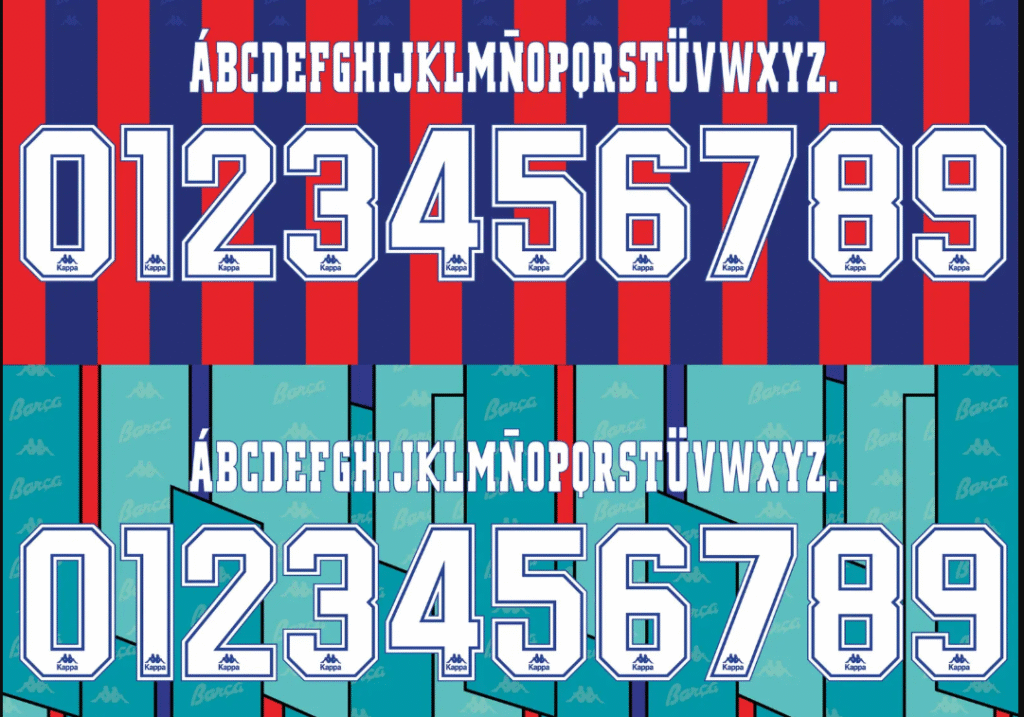
Fonte FC Barcelona 1995-1997 (Kappa) – A Era Ronaldo Fenômeno | Download TTF
Se existe uma época dourada que desperta a nostalgia de qualquer torcedor Blaugrana, é o meio da década de 90. Sob o comando da fornecedora Kappa, o F.C. Barcelona desfilou nos gramados europeus com uniformes que se tornaram verdadeiros ícones da cultura do futebol.
Neste post, trazemos para você a tipografia lendária utilizada entre as temporadas de 1995 e 1997. Esta é a fonte que estampou as costas de lendas como Pep Guardiola, Luís Figo, Stoichkov e, claro, a temporada avassaladora de Ronaldo Fenômeno (1996/97). É o arquivo essencial para quem deseja recriar com perfeição a magia do Camp Nou daquele período.
Estilo Visual: A Estética Clássica da Kappa
A tipografia do Barcelona dessa era reflete a identidade visual marcante da Kappa nos anos 90. Trata-se de uma fonte robusta, com serifas grossas e uma estrutura geométrica sólida (“block font”).
Visualmente, ela transmite força e tradição. Nos uniformes titulares (listras verticais Azul-Grená), os números eram geralmente aplicados em branco, muitas vezes com um sombreamento ou contorno preto para garantir o contraste. Já no icônico uniforme verde-água (Teal) da temporada 96/97, a fonte ganhava destaque em contornos vibrantes. É uma tipografia que carrega o peso histórico da Recopa Europeia e da Copa do Rei daquele ano.